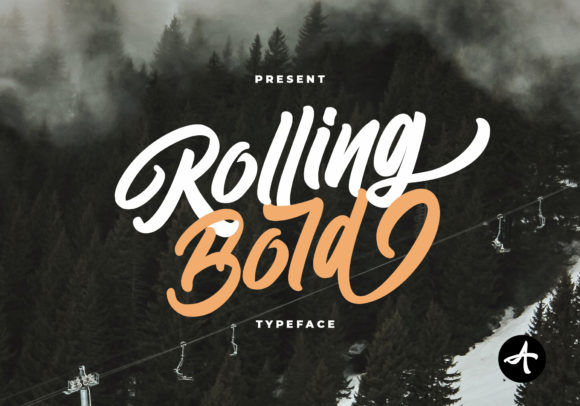
Rolling Bold
Rolling Bold : L'Écrivain Moderne Pour Créer des Conceptions Irresistibles
** **Un Script Moderne pour Donner un Coup de Pouce à Vos Conceptions
** Le **Rolling Bold** est une police d'écriture script moderne conçue pour rendre vos conceptions encore plus attractives. Éasy à utiliser, elle vous permettra de gagner du temps dans la création de vos designs. Cette police dispose également de nombreuses fonctionnalités OpenType telles que des ligatures et des alternatifs, ce qui la rend parfaite pour utiliser dans des conceptions telles que : **Applications de la Police Rolling Bold
** - **Logos** : Créez des logos uniques et attrayants qui vous feront se démarquer. - **Posters** : Utilisez la police Rolling Bold pour créer des posters qui attirent l'attention. - **Emballage** : Ajoutez un touché personnalisé à vos produits avec la police Rolling Bold. - **Marques de commerce** : Utilisez la police Rolling Bold pour créer des marques de commerce qui se démarquent. - **Médias sociaux** : Créez des publications sur les réseaux sociaux attrayantes avec la police Rolling Bold. - **Carnets de bébé** : Utilisez la police Rolling Bold pour créer des cartes de vœux personnalisées. **Avantages de la Police Rolling Bold
** - **Facile à utiliser** : La police Rolling Bold est conçue pour être facile à utiliser, même pour les non experts. - **Sécurité de la conception** : La police Rolling Bold est conçue pour vous aider à créer des conceptions attrayantes et professionnelles. - **Flexibilité** : La police Rolling Bold est compatible avec une variété de formats de fichier. **Découvrez le Rolling Bold